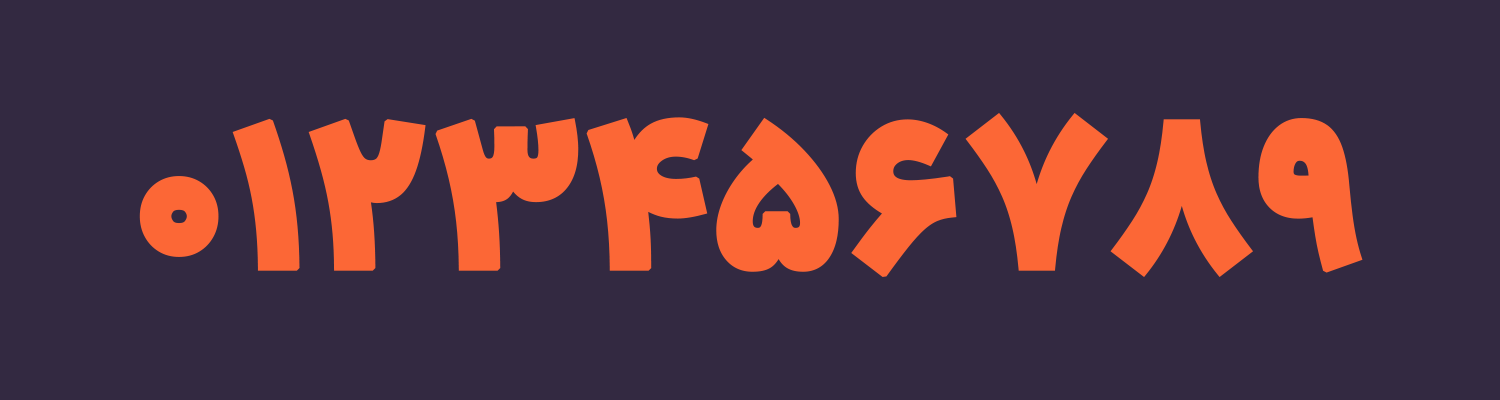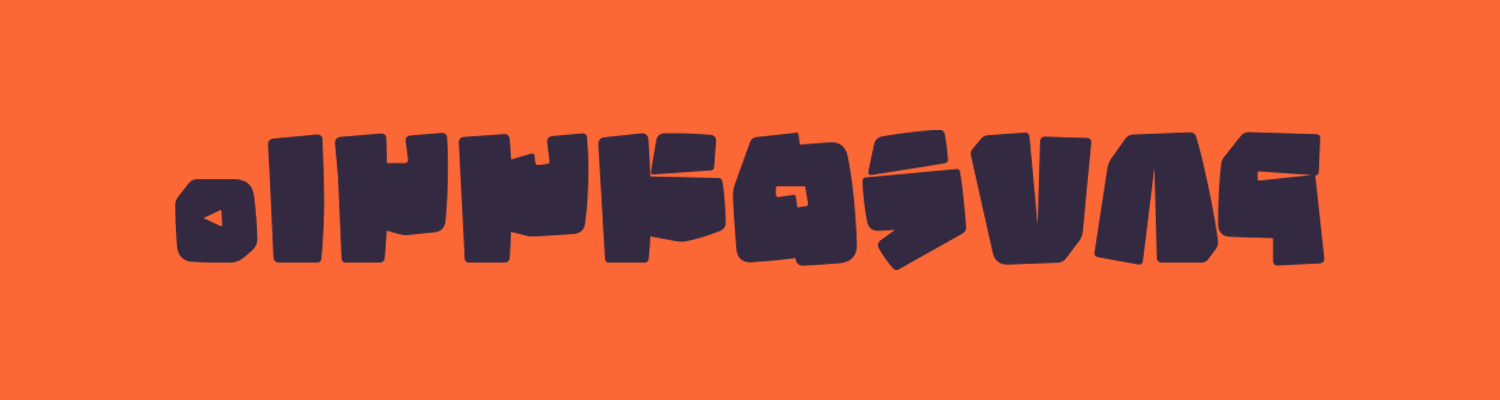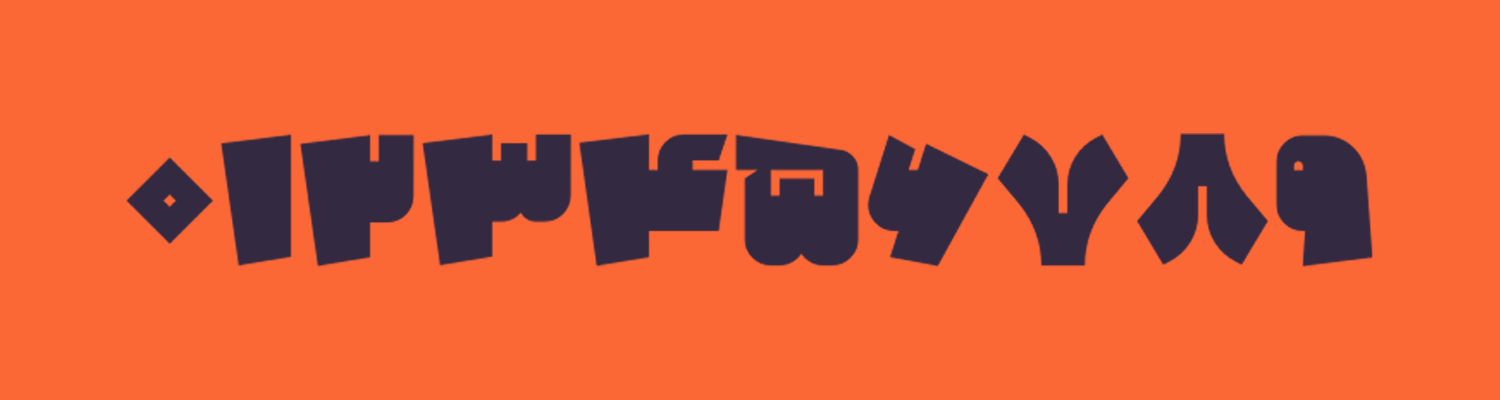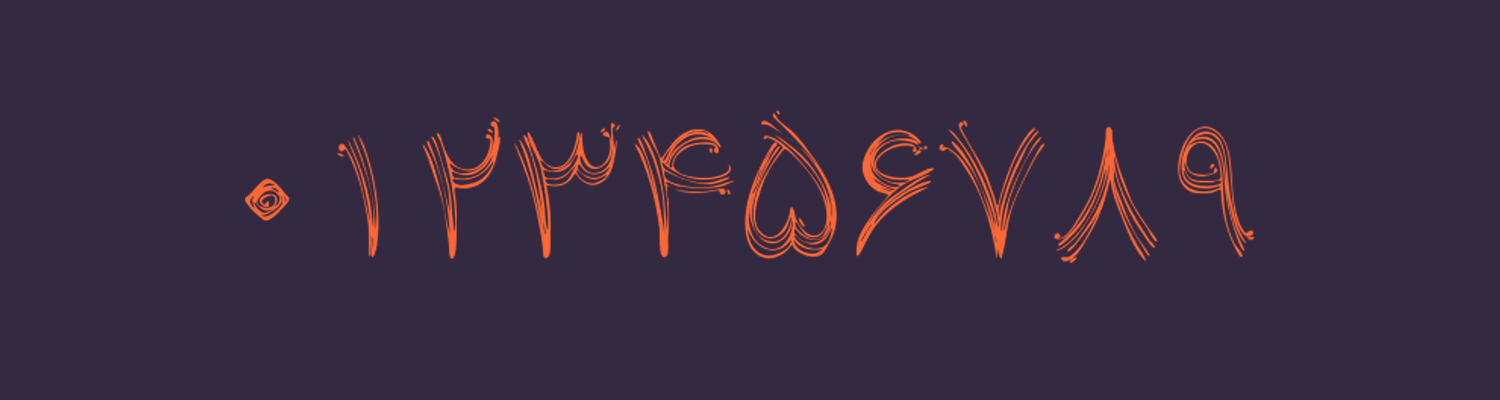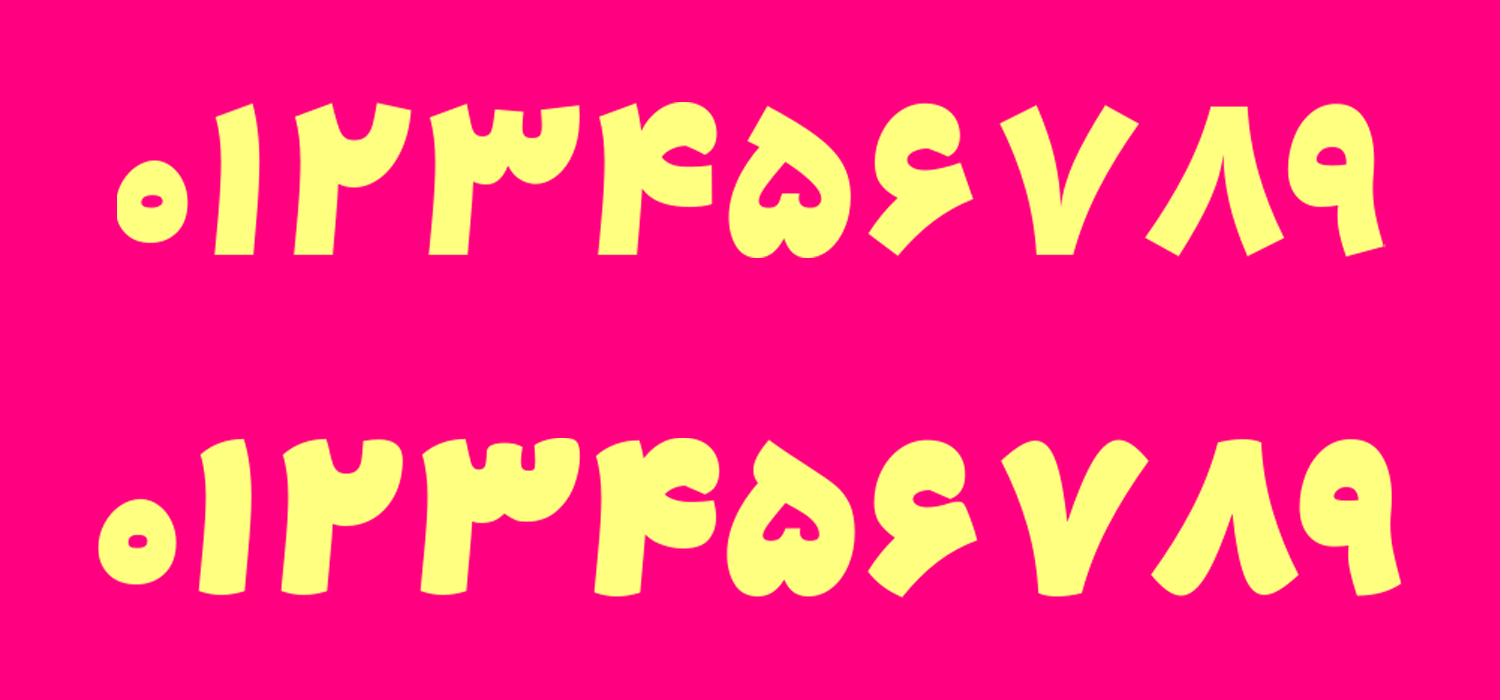
دانلود بهترین فونت اعداد فارسی (معرفی ۱۱ فونت)
استفاده از فونتهایی با اعداد فارسی علاوه بر ارائه ساختار استاندارد زبانی به نوشتههای شما، در زیباتر کردن آنها نیز تاثیر شگرفی دارد. فونت عدد فارسی تقریبا در بیشتر فونتهای این زبان وجود دارد؛ با این تفاوت که برخی قلمها استاندارد بوده و اعداد کاملا فارسی هستند و در برخی دیگر که عموما فونتهای قدیمی هستند، اعداد عربی «٤٥٦» گنجانده شده است. از همینرو در این مقاله به معرفی بهترین فونت اعداد فارسی خواهیم پرداخت.
در میان انبوه فونتهای فارسی که این روزها توسط طراحان فونت فارسی ارائه شده است؛ قلمهایی در سبکهای مختلف را میبینیم که هر کدام در بخش اعداد نیز دارای گلیفهایی به همان سبک فونت هستند. استفاده از همان سبک طراحی فونت نیز در بخش اعداد لزوما باید رعایت گردد تا در صورت استفاده از اعداد درون نوشتهها باعث دوگانگی ساختاری نشود.
لذا در ادامه این نوشته از وبلاگ فونتچی به معرفی 9 تا از بهترین فونتهای فارسی که سبک خاص و زیبایی از اعداد را دارند معرفی خواهیم کرد که میتوانید در پروژههای خود از این قلمها استفاده کنید.
دانلود بهترین فونت اعداد فارسی
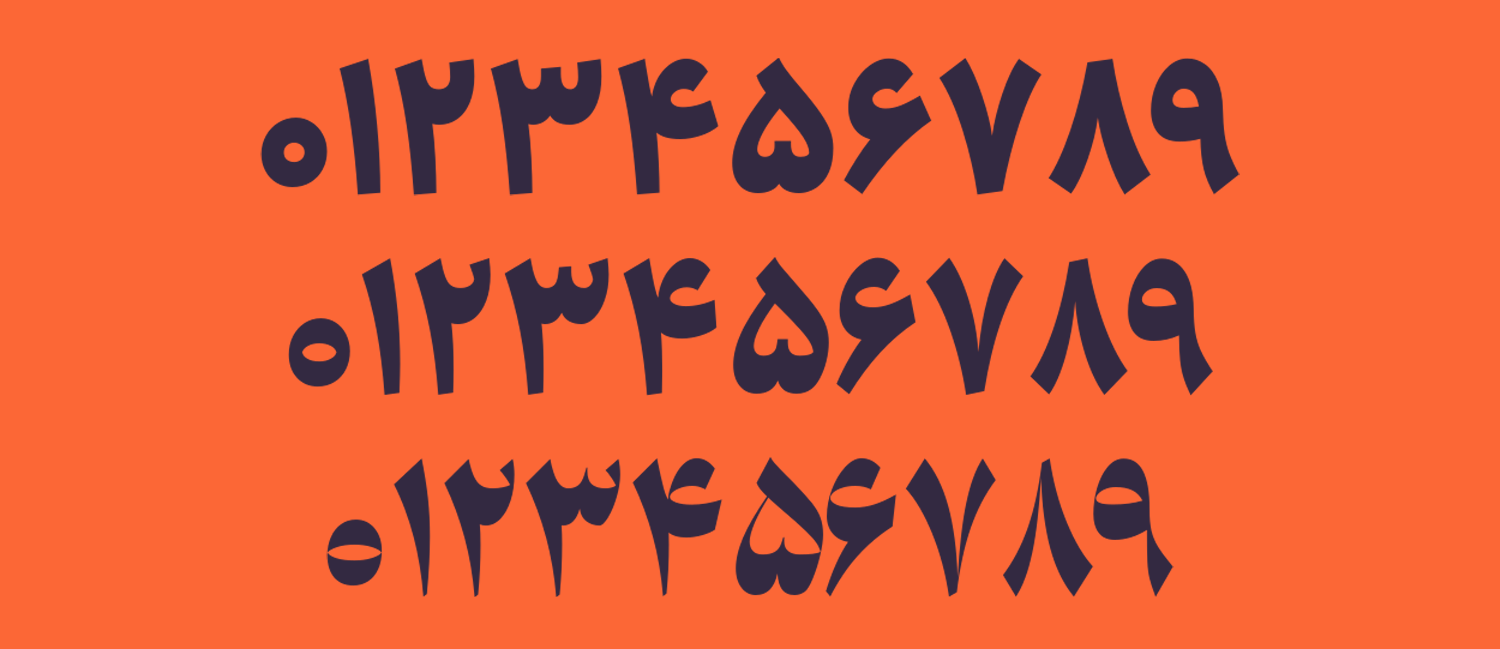
فونت ابر
فونت ابر قلمی در ۵ وزن است که تمامی این وزنهای پنجگانه از ۳ سبک پشتیبانی میکنند. این سبکهای سهگانه سه حالت مختلف را از نظر کنتراست برای فونت فراهم کرده است که شامل نسخه کم، متوسط و زیاد است.
اعداد در این فونت نیز به همینترتیب است. با استفاده از سبک کم یا Low میتوانید ساختاری با ضخامت کم را در اختیار داشته باشید که نقاط پایان خطوط عمود، گردیها و شکستگیها در تمامی اعداد از حالت فشرده به نازک تغییر حالت داده است. به همین ترتیب با تغییر سبک به حالات میانه (Mid) و بالا (High) این ضخامت بیشتر خواهد شد و از کنتراست فونت با گوشهها و خطوط تیز کاسته میشود.
این فونت از نظر اعداد ساختاری زیبا را به متن شما خواهد داد. بهویژه زمانی که از وزنهای بالا در کنار سبک High استفاده کنید ساختاری بسیار نرم را در اختیارتان قرار خواهد داد.
فونت هستی با اعداد نستعلیق
فونت هستی را میتوان یکی از زیباترین قلمها با اعداد فارسی معرفی کرد. این فونت که در ظاهر کاملا شبیه به نستعلیق بهنظر میرسد، اما برخلاف آن نستعلیق نبوده و میتوان گفت نسخهای امروزی از خط نستعلیق را شامل میشود که با افزوده شدن ضخامت بسیار بیشتر در کنار دستکاریهای گسترده در زوایا و منحنیها به این شکل طراحی شده است.
اعداد فارسی فونت هستی بیانگر اصالت خط فارسی بوده و استفاده از آن را در کارهای گرافیکی در فضای دیجیتال پیشنهاد میکنیم. خصوصا برای تصویر تامنیل در شبکههای اجتماعی نظیر اینستاگرام و یوتوب که استفاده از چنین فونت عنوانی میتواند موجب بالا رفتن نرخ کلیک و افزایش بازدید گردد.
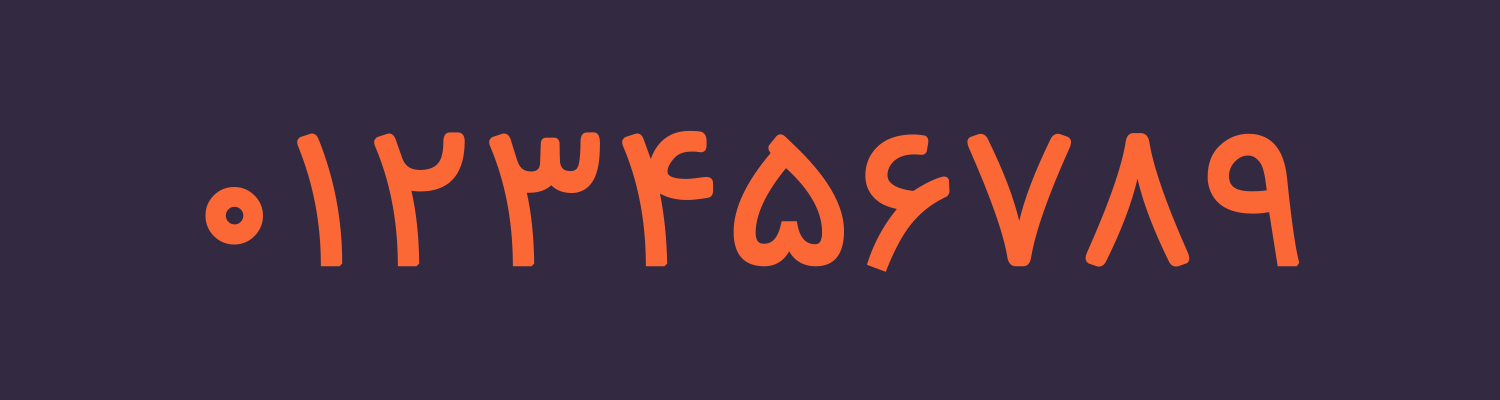
فونت عدد فارسی رایگان تنها
اگر به دنبال بهترین فونت اعداد فارسی با سبک دستنویس هستید، فونت تنها که توسط مرحوم صابر راستی کردار طراحی شده است میتواند انتخاب خوبی برای استفاده در وب و اپلیکیشن باشد.
فونت تنها در عینحال که ساختاری بسیار ساده دارد، استخوانی به نظر رسیده و همچنین خوانایی خوبی در سایزهای بزرگ نیز دارد. استفاده از این فونت برای اپلیکیشنهایی که با اعداد و ارقام زیادی سر و کار دارند میتواند انتخاب بهتری باشد.
به عنوان نمونه در صرافیهای ارز دیجیتال یا بورس که رقمهای مختلفی برای نوسانات قیمتی، حجم بازار و… وجود دارد استفاده از فونتی که اعداد آن نسبت به فونت بدنه کوچکتر باشد توصیه میشود.
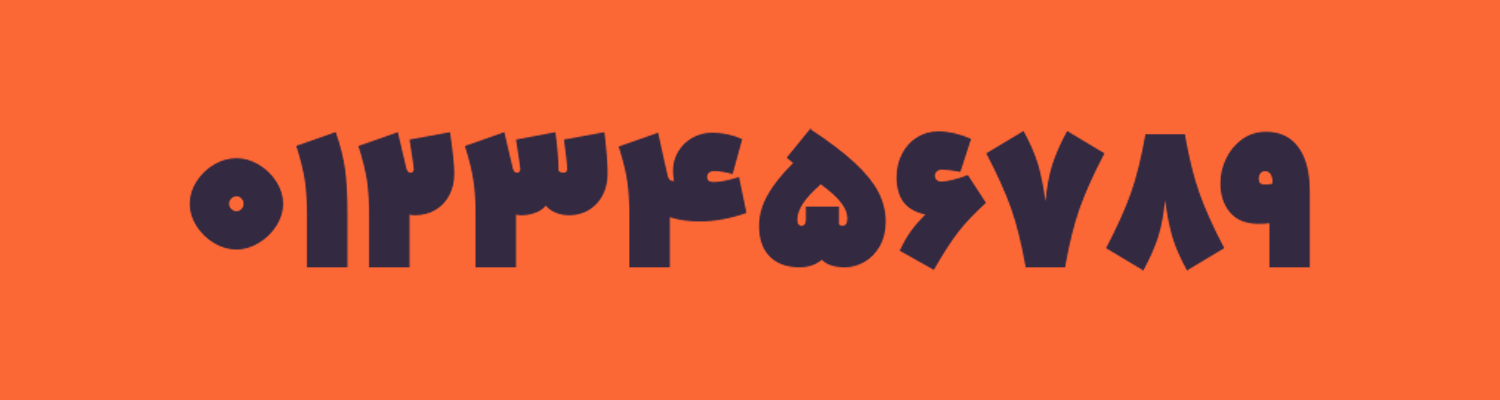
فونت یکان بخ
فونت یکان بخ نیز یکی دیگر از فونتهایی است که در بخش اعداد بهخوبی روی آن کار شده است. علاوه بر اینکه در تمامی وزنها و سبکها اعداد شکل کاملا استانداردی با حروف دارند، امکان استفاده از برخی اعداد را با ظاهر متفاوت نیز در اختیار خواهید داشت که البته برخی از آنها نیز شامل حروف عربی هستند.
اعداد فارسی فونت یکانبخ برای استفاده در محیطهای تبلیغاتی اثرپذیری بالایی روی مخاطب خواهند داشت. خصوصا در بیلبوردهای تبلیغاتی درون شهری که لزوما استفاده از فونتی با سایز و وزن بزرگتر در کنار رنگبندی مناسب میتواند بیشتر موجب جلب توجه شود.
دندانهها و منحنیهای اعداد در این فونت ساختاری کاملا نرم و در عینحال ضخیم دارند که به خوانایی بیشتر متن، بهویژه در اندازهها و وزنهای بزرگ کمک میکند.
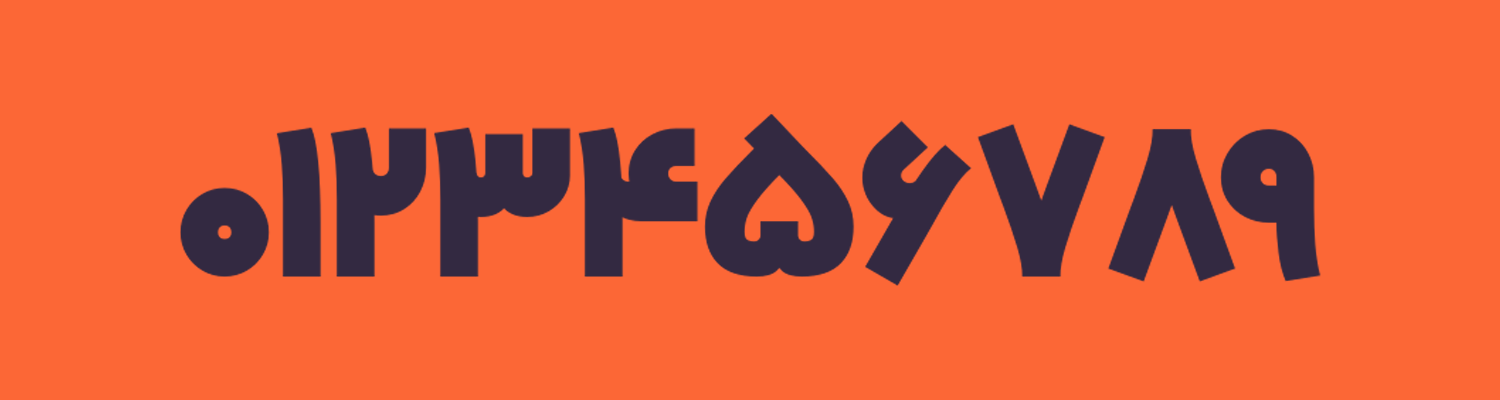
فونت کلمه
فونت کلمه نیز یکی دیگر از قلمهای مناسب برای استفاده از اعداد فارسی است. در این فونت اعداد نسبت به فونتهای دیگری مثل یکانبخ ضخامت کمتری دارد، با اینکه برای استفاده در فضاهای تبلیغاتی هم مناسب هستند، اما توصیه میشود از این فونت بیشتر در فضای چاپ استفاده کنید.